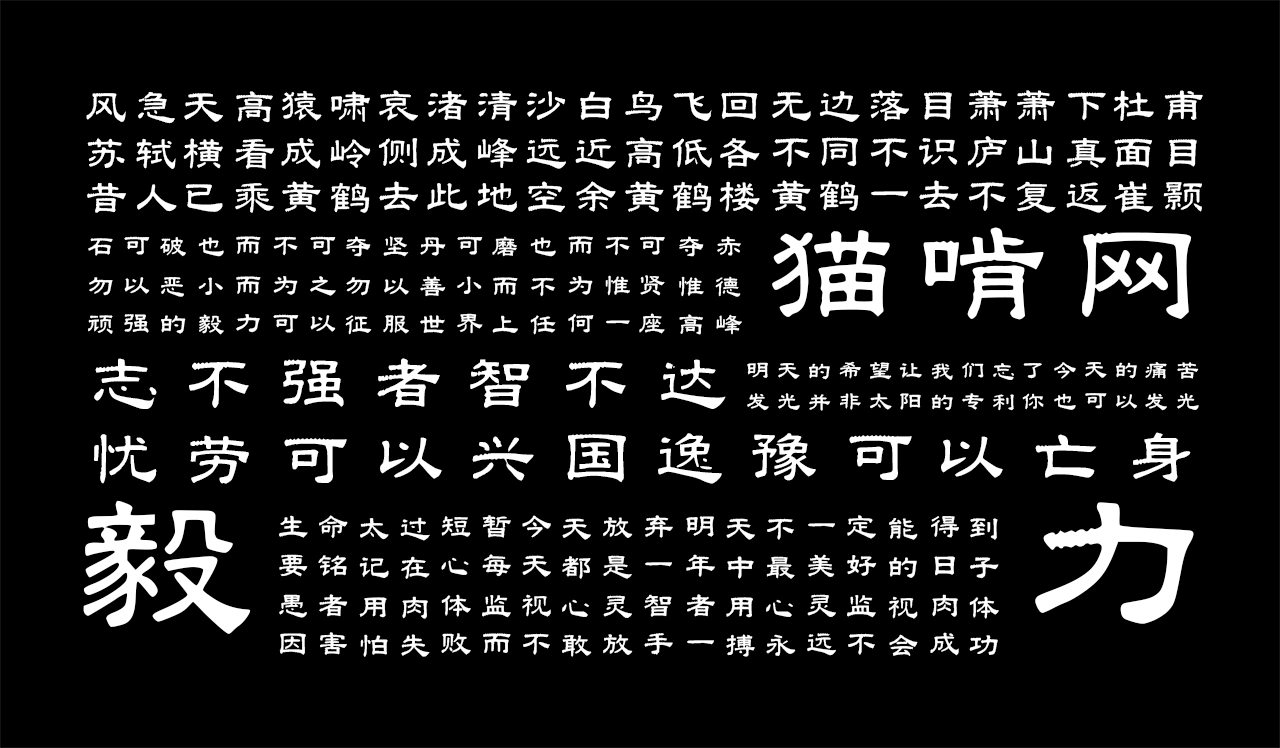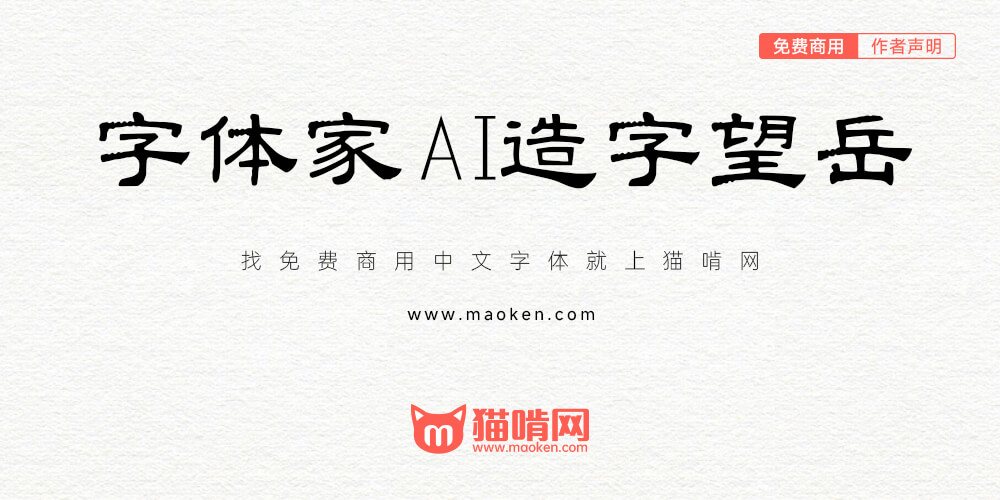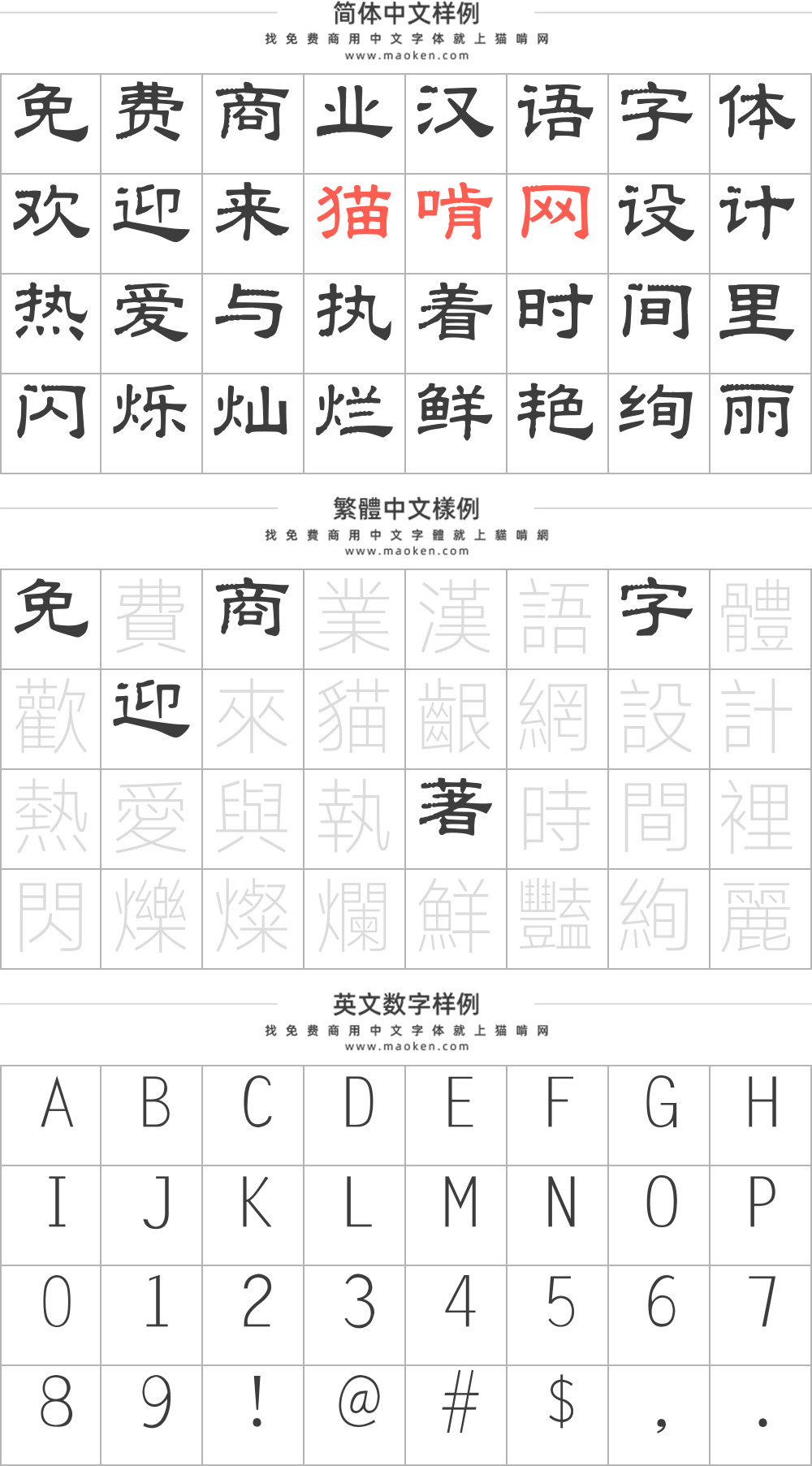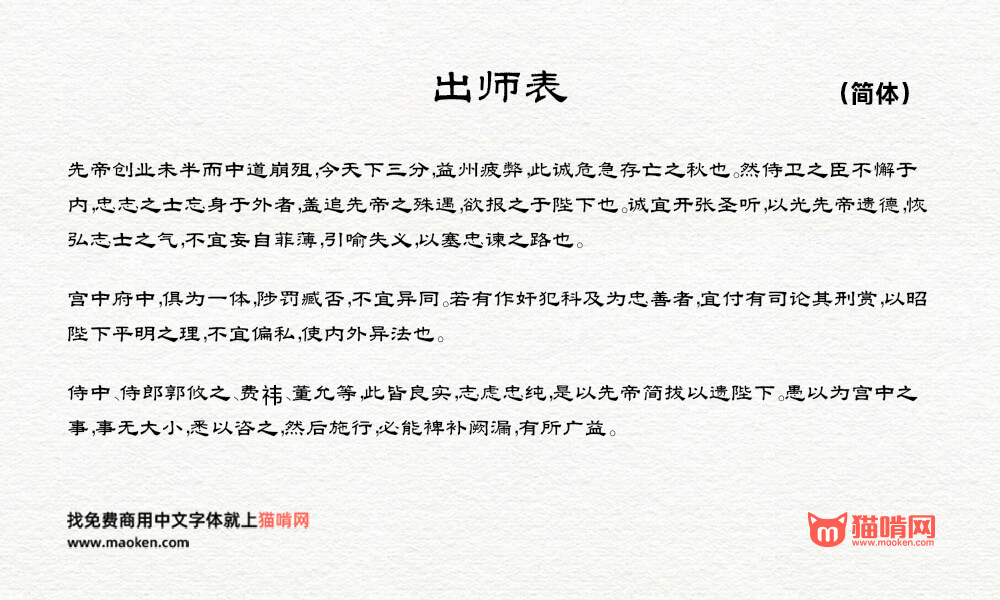
字体家AI造字望岳:一款由字体家AI神笔造字生成的一款艺术字体
字体家AI造字望岳是一款由字体家AI神笔造字生成的一款艺术字体,此字体横画起笔略顿,收笔利落如切刀,竖画挺拔似柱,粗细均匀中藏筋骨。转折处方硬见棱角,又带微圆过渡,不生硬。结构重心沉稳,笔画边缘干净,兼具黑体的规整与手写的力道,像稳健的山石,端庄中透着坚实,给人可靠、大气、有分量的美感。适合用于广告、海报设计,平面设计等。
这款字体总体感观不错,我下载试了一下,绝大部分字体都有锯齿,希望能优化一下,或者,给使用者提供一个优化的路径,我是用这个字库,用了十余个字,很多都有锯齿,必须花时间修改后才能用,如果给一个路径,很多使用者把优化后的字体上传,就能集中广大网友共同优化这个字库》
锯齿,可惜了……
(嗯,还有侵权风险?那更可惜了,可惜得不能再可惜了……吧?)
这款字体与大萌汉体90%相近,建议不要用于商用,有侵权风险,给大家提醒一下
比较少见的隶书风格字体,比方正华文之类的隶书体好看
字体家AI造字望岳; 字体确实很不错,使用价值很广泛。但是不适合大字体使用,也不适合在电脑上看:较多字行的 横 笔,有明显的连续波浪形锯齿,削弱了字形气势。另外,建议 还是 换个正经点、简短点的字体名吧,哪怕就叫 字体家望岳体 也好。
• 我觉得就叫:“字体家AI造字望岳体”就已经很好了,本来就是“AI生成的字体”为啥要隐藏标签?